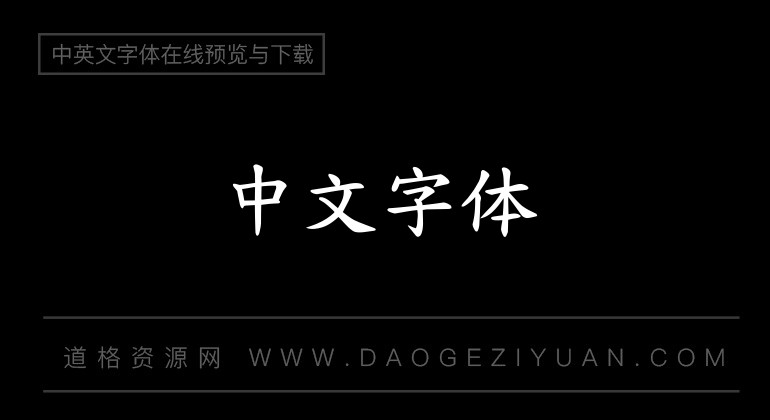
博洋楷体7000是一款中文字体,由博洋字体设计公司设计,于2018年发布。它是一款经典的楷体字体,具有良好的结构、视觉效果和技术性能。字体采用精细的曲线设计,为汉字字体提供了更加清晰、精细的视觉效果,并且拥有更强的抗锯齿能力和更强的可读性。此外,字体还支持多种字体格式,可以满足不同的使用场景,比如桌面、网页、手机应用等。文件名:BoYangKaiTi7000-1.ttf
博洋楷体7000是一款非常不错的手写艺术字体,具有很好的视觉感,适合于文化类的宣传设计、商业类品牌的广告和产品包装设计以及个性化文字排版等较多场景。